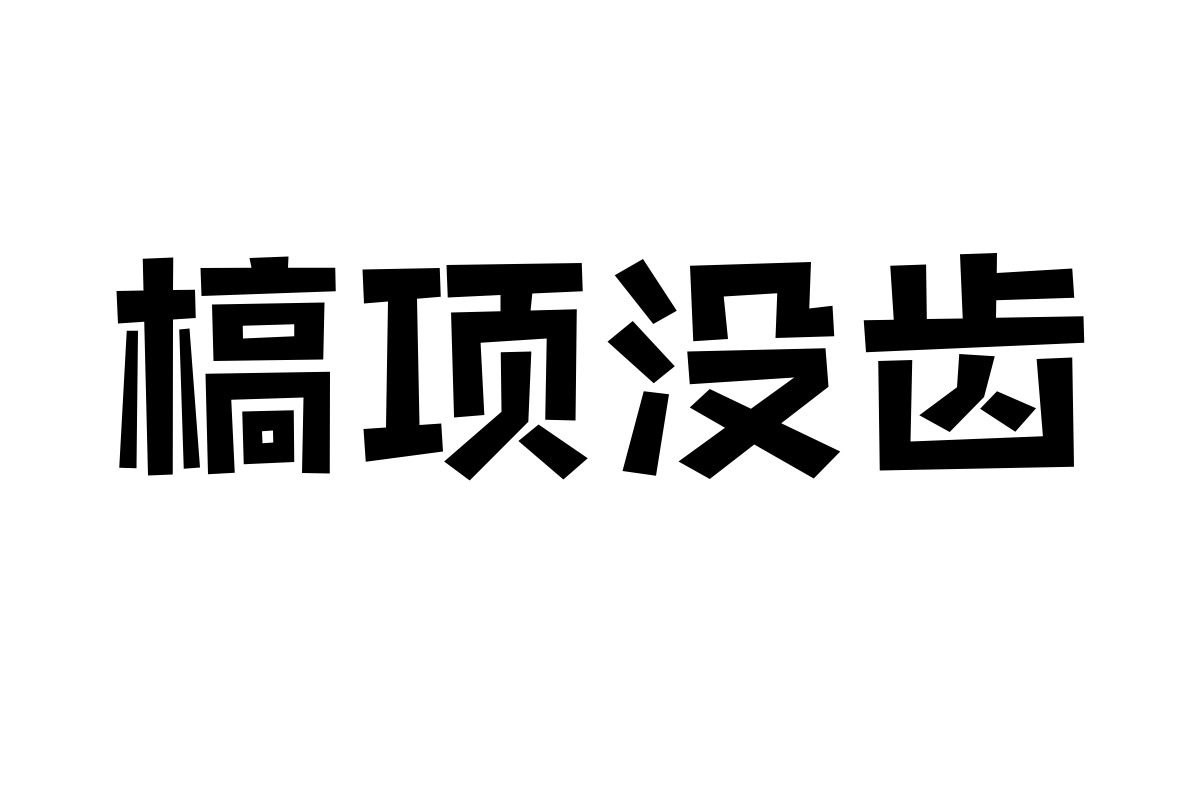
本墨剪字字体是由北京本墨文化传媒有限公司设计的一款创意中文字体。这款字体采用了独特的剪影风格,将汉字的轮廓和线条进行艺术化处理,使其更加简洁、明快、富有现代感。同时,字体中还融入了一些传统文化元素,如篆刻、书法等,使得整体风格更具特色。
本墨剪字字体适用于各种设计场景,如海报、广告、包装等,能够为作品增添一份独特的韵味。